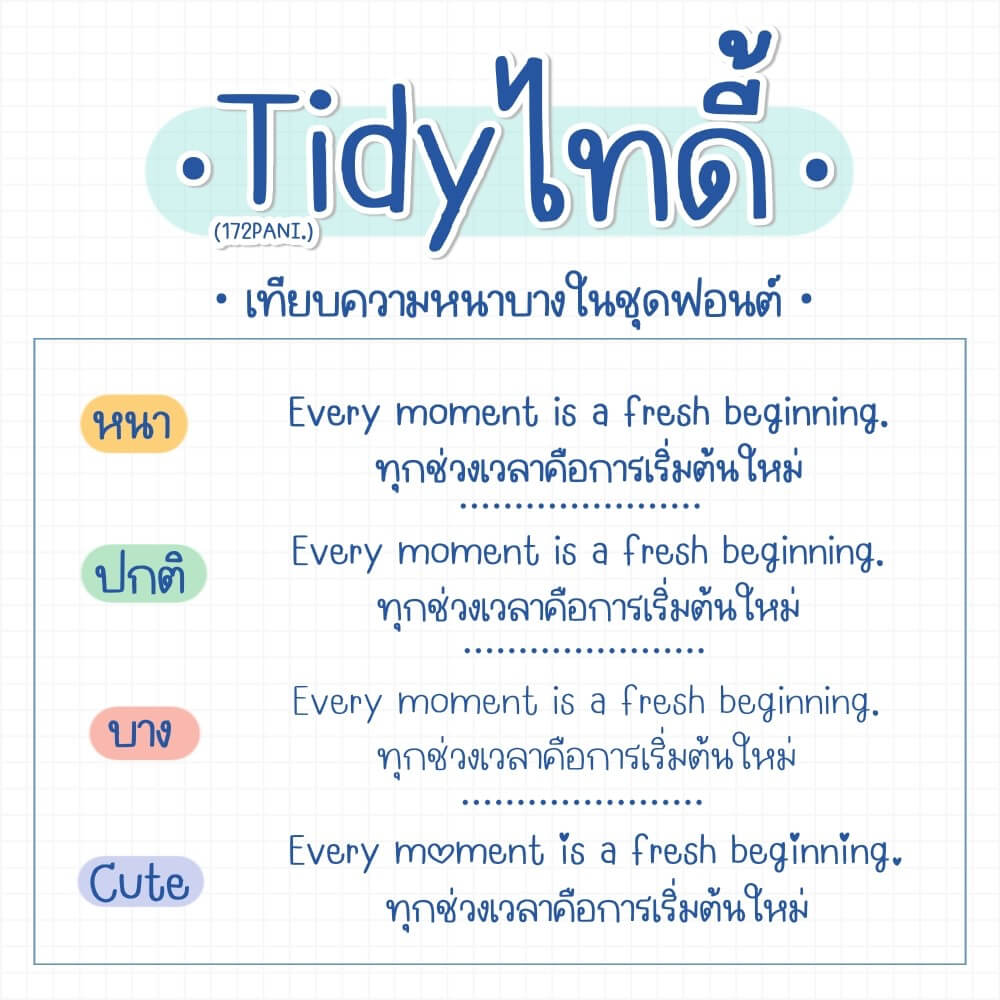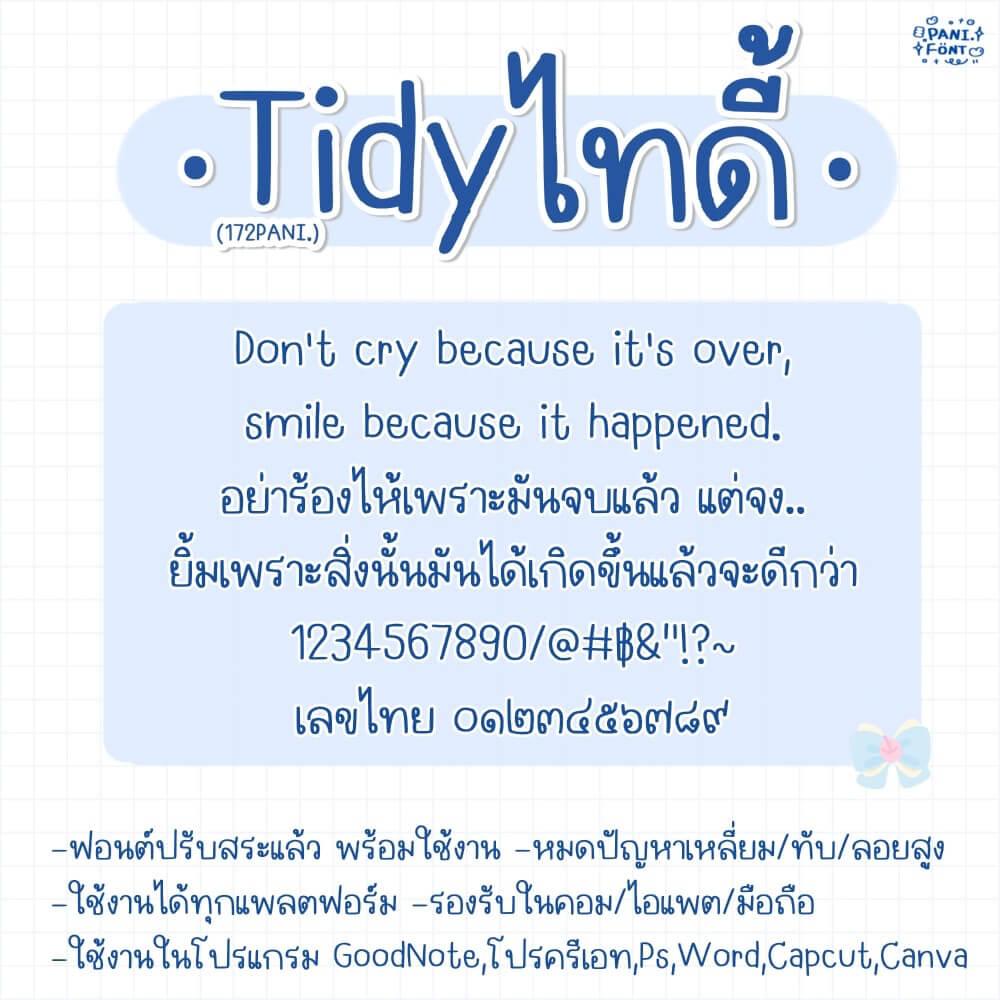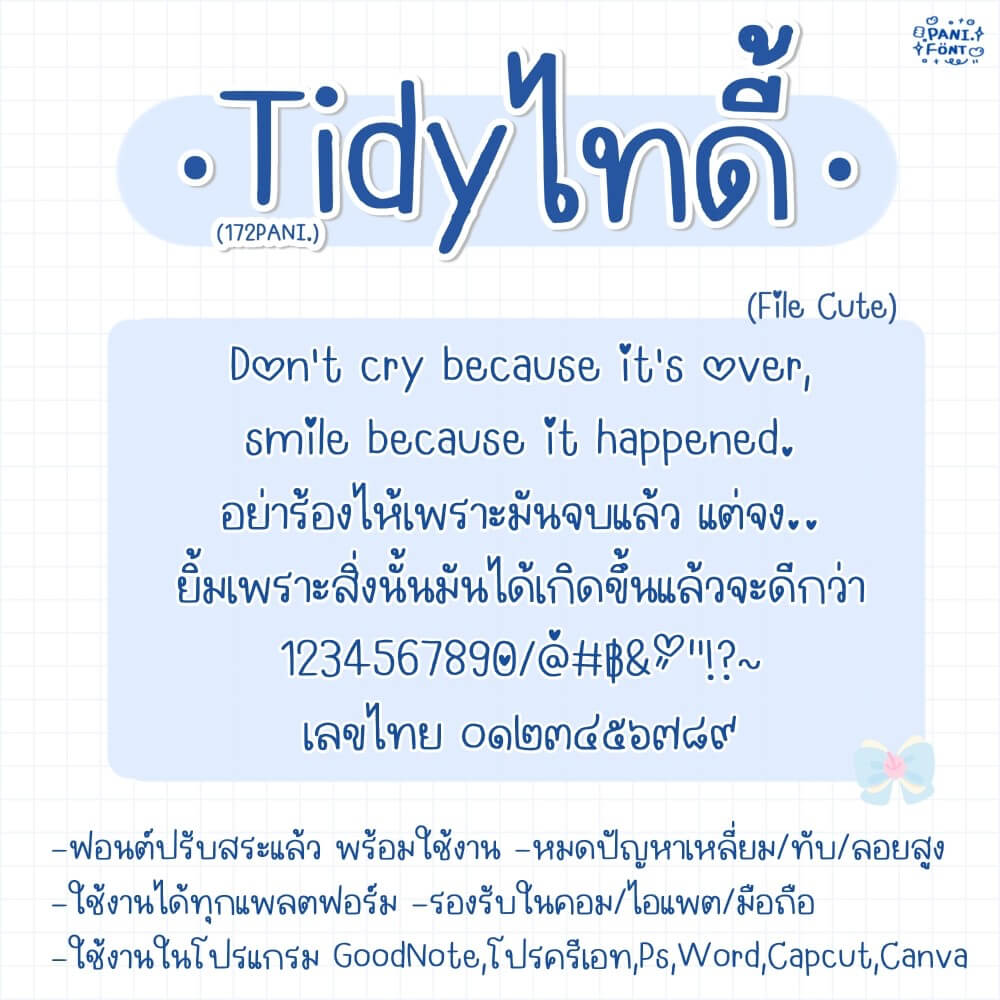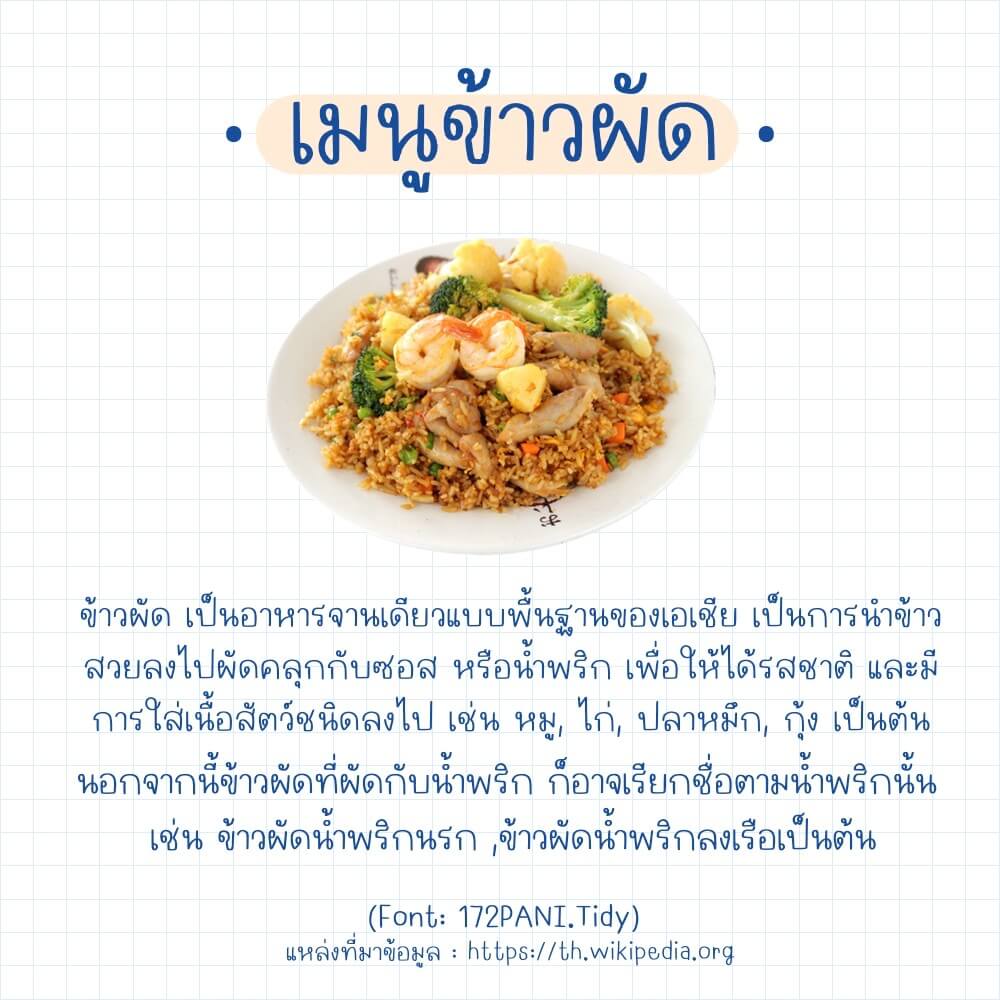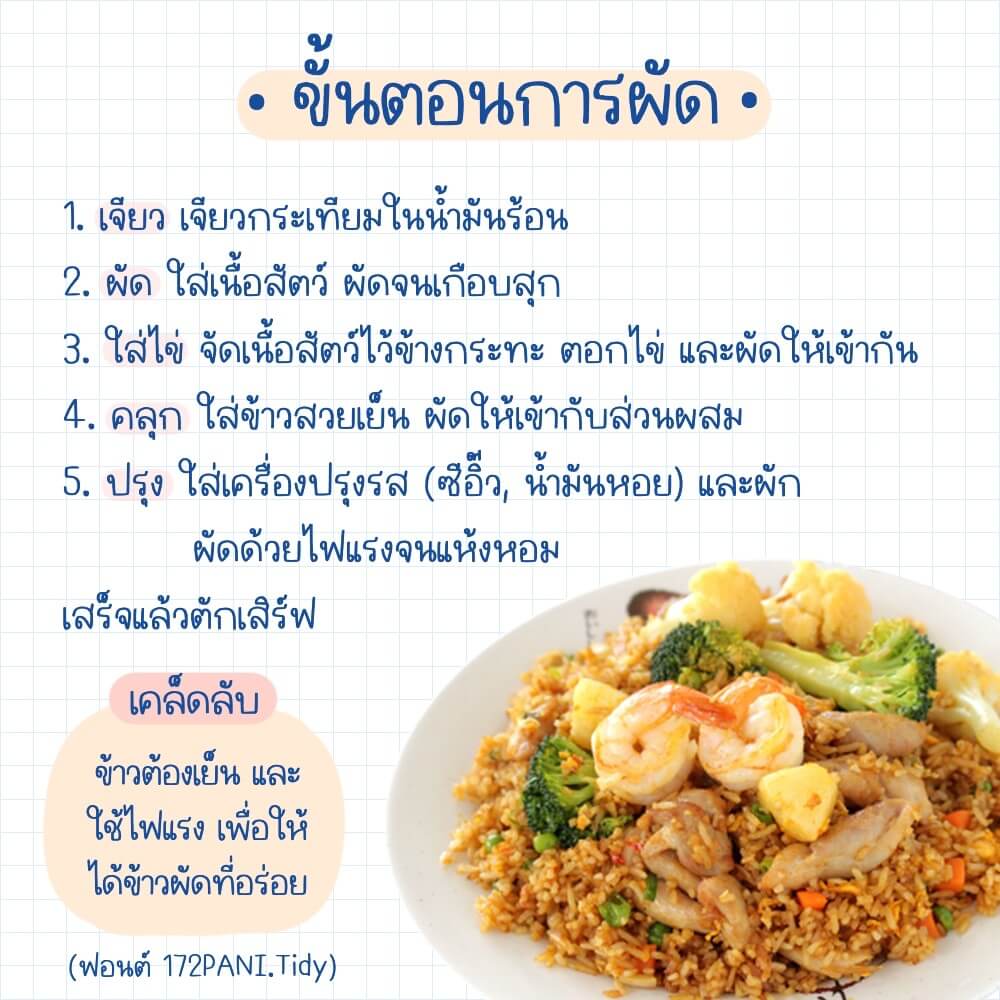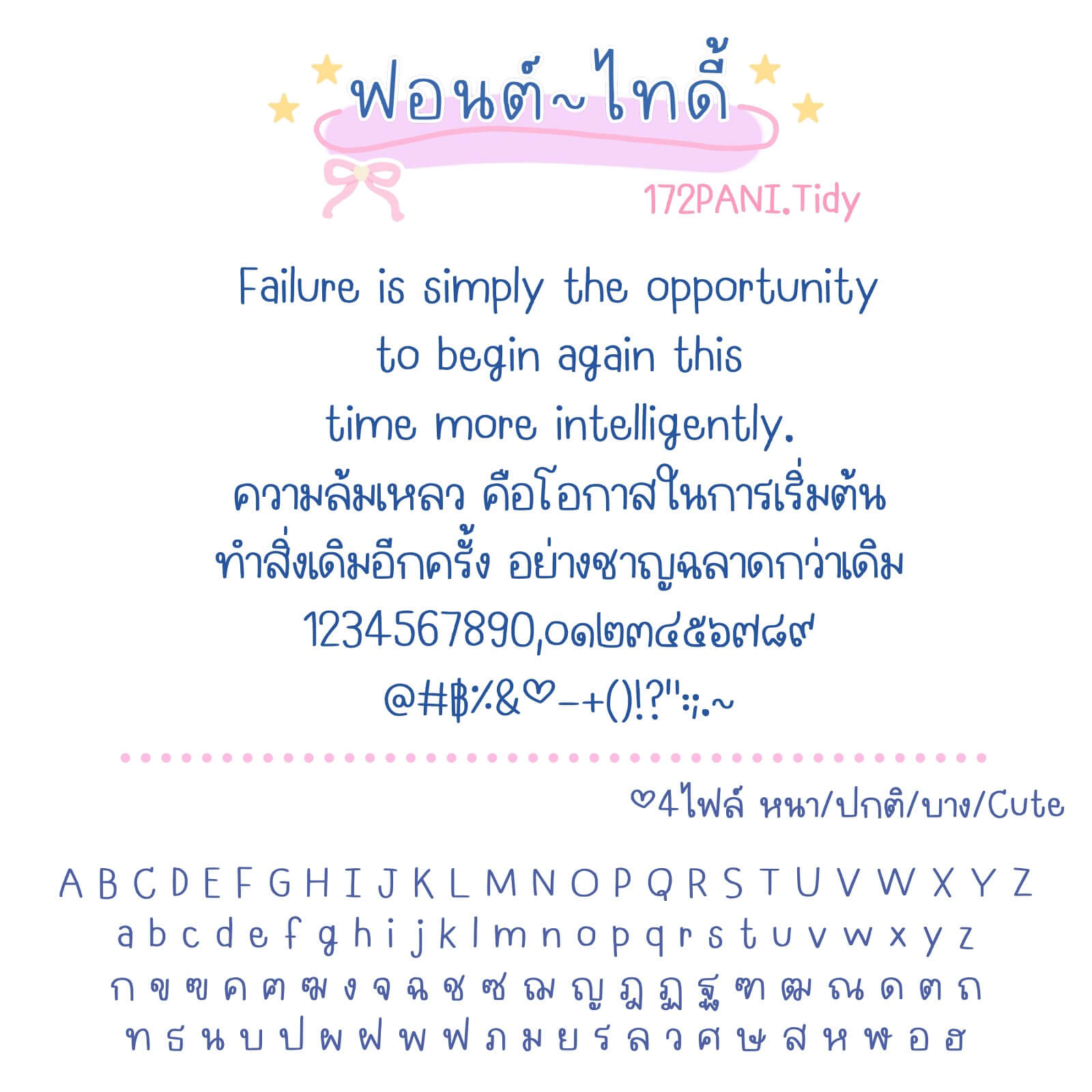
172PANI.ไทดี้
ฟอนต์ 172PANI.ไทดี้ – ฟอนต์แนวเรียบร้อย เส้นบาง กึ่งทางการ เหมาะกับการใช้งานรายละเอียด ใบงาน มีความทันสมัย สวยงาม แต่ยังคงเรียบร้อย
ฟอนต์มี 4 ไฟล์ – น้ำหนัก บาง ปกติ หนา Cute